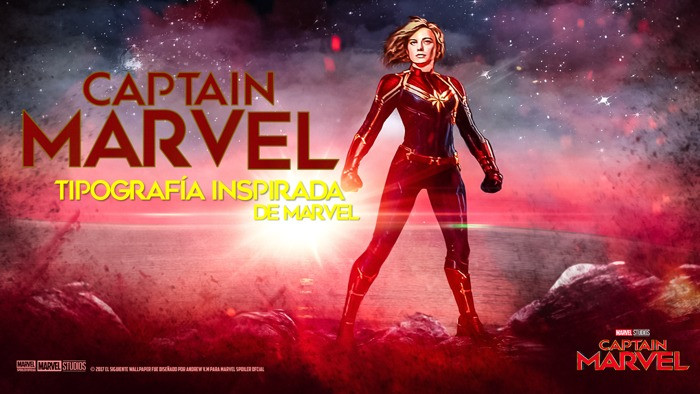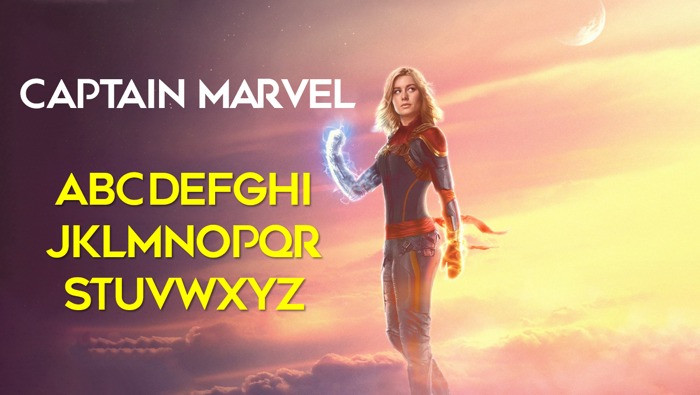
Captain Marvel Sans Serif Font
Tipografía de la película CAPTAIN MARVEL
Typography of the film CAPTAIN MARVEL
Tipografía de la película CAPTAIN MARVEL
Typography of the film CAPTAIN MARVEL